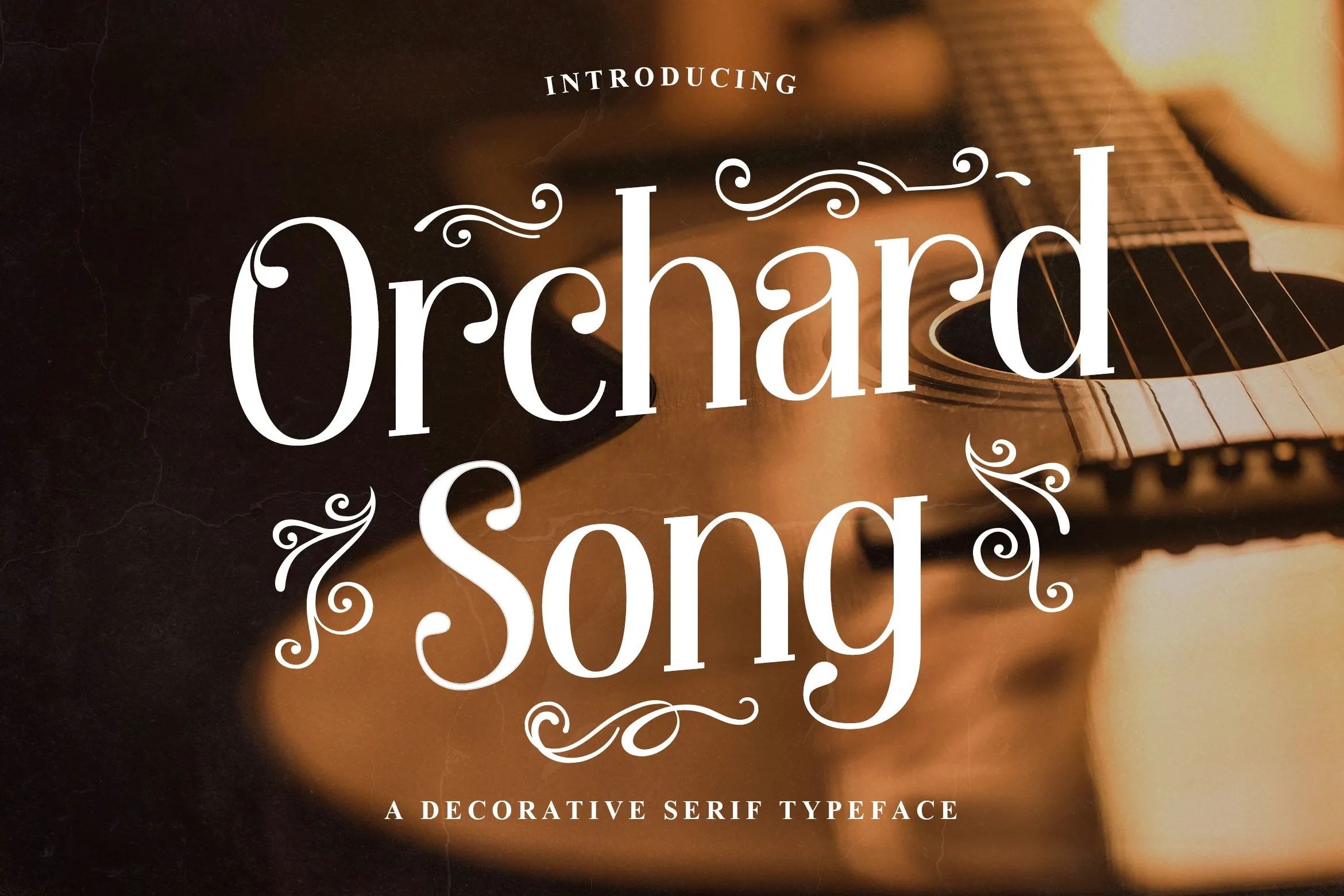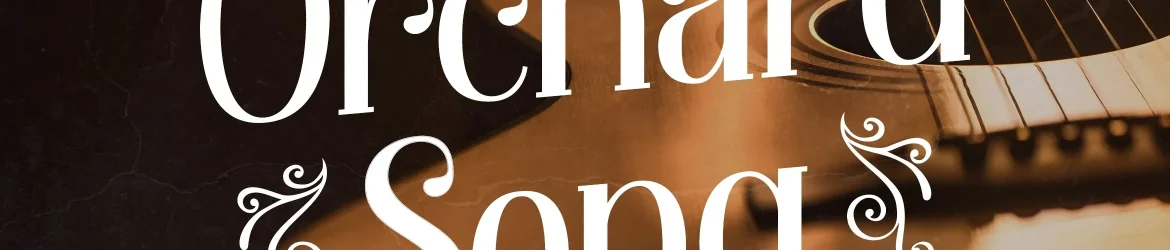
A fonte ‘Orchard Song Font’ oferece uma paleta vibrante de letras serifas modernas e fortes, com diversos ligaduros e alternativas que irão dar um toque ainda mais estilizado às suas apresentações ou logomarcas. Este design elegante é perfeito para projetos com temas musicais ou instrumentais, trazendo uma vibe especial que destaca sua personalidade. Ideal tanto para necessidades pessoais quanto para propostas promocionais e desafios criativos, seja em scrapbooking, impressão ou qualquer projeto que você imagine. ‘Orchard Song Font’ é a fonte perfeita para levar suas ideias à nova dimensão graças às suas características inovadoras.